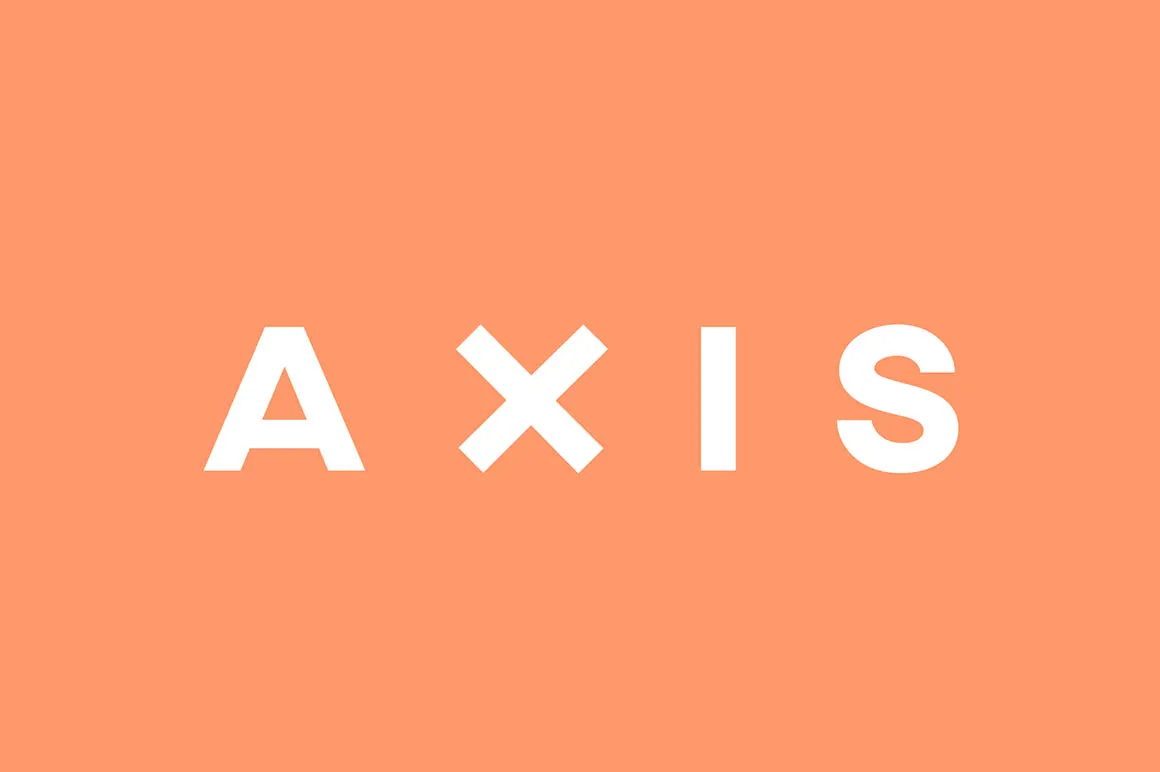
AXIS Typeface – Fonte Grátis
AXIS Typeface
A fonte ‘AXIS Typeface’ traz uma experiência clara e direta para seu design. Desenvolvida pelo designer Hamilton, esta fonte sans-serif está disponível em todas as letras maiúsculas, criando um estilo moderno e minimalista perfeito para textos de página web ou qualquer aplicação digital onde você precisa de uma aparência simples e profissional. Sem qualquer adição estilística superflua, a ‘AXIS Typeface’ é uma escolha ótima para projetos que valorizam uma linguagem clara e moderna. Seja em artigos informativos, designs gráficos ou sites, essa fonte vai se destacar por sua simplicidade e eficácia. Descubra mais sobre como a ‘AXIS Typeface’ pode transformar seus trabalhos digitais ao acessar bit.ly/axis-typeface.